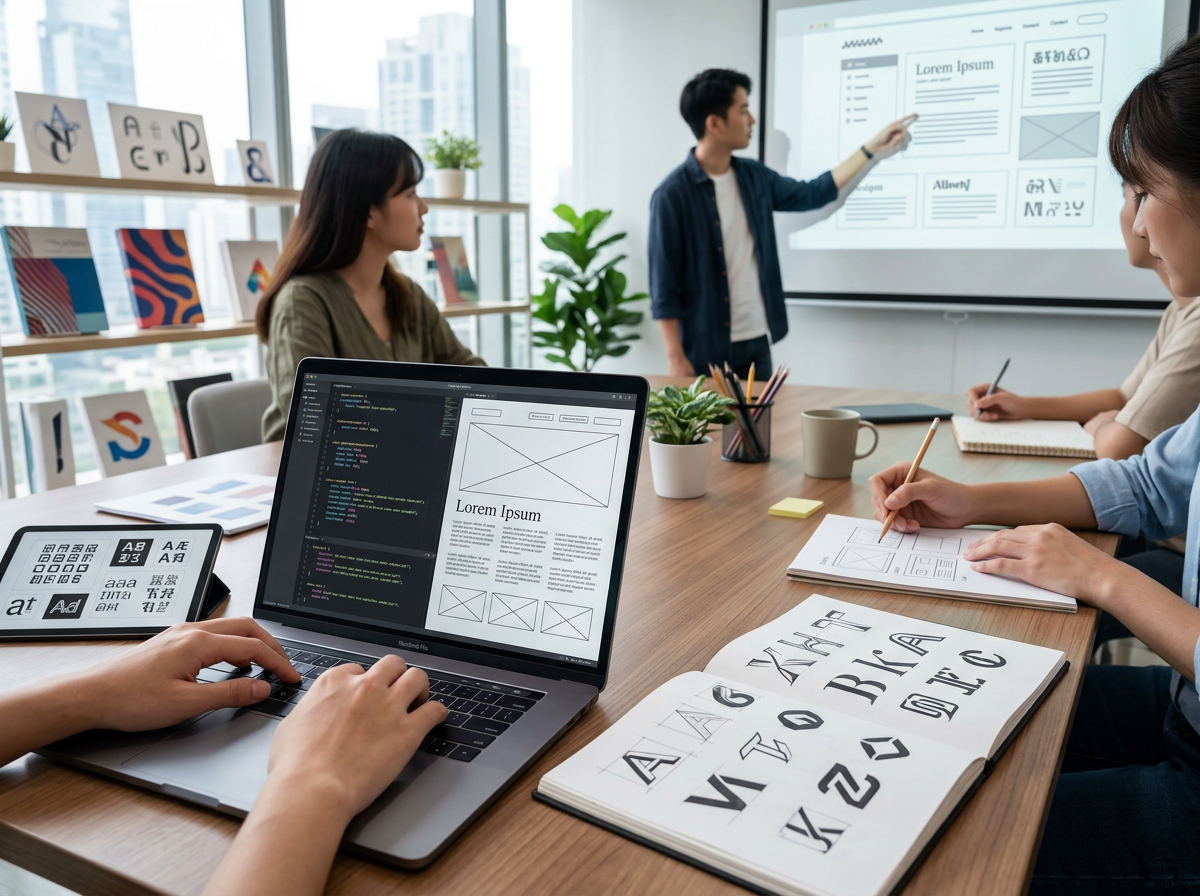
Kostenlose Schriftarten für Webseiten: Effiziente Auswahl und Integration
Der erste Blick auf eine Webseite entscheidet oft über Verweildauer und Nutzererfahrung. Eine passende Typografie prägt diesen Eindruck maßgeblich, vermittelt Professionalität oder Kreativität. Doch die schiere Menge an verfügbaren Optionen überfordert viele Gestalter.
Oftmals greifen Webdesigner zu Standardlösungen, die zwar funktional sind, aber dem Projekt eine individuelle Note verwehren. Die Suche nach der idealen Schriftart, die sowohl ästhetisch ansprechend als auch technisch optimiert ist, erweist sich als zeitaufwendig.
Dieser Leitfaden beleuchtet die Kriterien für die Auswahl kostenloser Schriftarten für Webseiten und zeigt auf, wie diese effizient in digitale Projekte integriert werden. Erfahren, welche Aspekte bei der Typografie für das Web entscheidend sind und wie sich gängige Fehler vermeiden lassen.
Kurz zusammengefasst
- Die Wahl der Webfont beeinflusst die Nutzererfahrung und Markenwahrnehmung erheblich.
- Ladezeiten und Dateigröße sind entscheidende technische Faktoren bei der Schriftauswahl.
- Google Fonts bietet eine umfangreiche Bibliothek mit einfacher Integration.
Welche Kriterien sind bei der Auswahl von Webfonts entscheidend?
Bei der Auswahl von Webfonts sind primär die Lesbarkeit, die Ästhetik und die technische Performance ausschlaggebend. Eine Schriftart muss auf verschiedenen Bildschirmgrößen und Auflösungen gut lesbar sein, um eine optimale Nutzererfahrung zu gewährleisten.
Die Ästhetik einer Schriftart sollte die Markenidentität widerspiegeln und die gewünschte Botschaft visuell unterstützen. Technische Aspekte wie die Dateigröße und die Unterstützung verschiedener Schriftschnitte beeinflussen maßgeblich die Ladezeiten der Webseite.
Lesbarkeit auf unterschiedlichen Geräten
Die Lesbarkeit einer Schriftart auf digitalen Bildschirmen stellt eine fundamentale Anforderung dar. Dies betrifft insbesondere die Darstellung auf mobilen Endgeräten, wo kleinere Schriftgrößen und geringere Auflösungen die Erkennbarkeit erschweren.
Serifenlose Schriften, sogenannte Sans-Serif-Fonts, erweisen sich hier oft als vorteilhafter, da die klaren Linien und das Fehlen von Zierelementen die Lesbarkeit bei geringer Pixeldichte verbessern. Die Buchstabenformen müssen auch in kleinen Punktgrößen klar differenzierbar bleiben.
Ein weiterer Aspekt ist die X-Höhe, also die Höhe der Kleinbuchstaben im Verhältnis zu den Großbuchstaben. Eine größere X-Höhe trägt zur besseren Lesbarkeit bei, da die Buchstabenformen deutlicher hervortreten.
Technische Aspekte und Performance
Die technische Seite der Schriftartenintegration beeinflusst die Ladezeit einer Webseite erheblich. Jede zusätzliche Schriftdatei erhöht das Datenvolumen, das der Browser herunterladen muss, was sich direkt auf die Performance auswirkt.
Optimierte Webfonts, die in verschiedenen Formaten wie WOFF2 vorliegen, reduzieren die Dateigröße signifikant. Die Auswahl von Schriftarten mit nur den benötigten Schriftschnitten – beispielsweise nur Regular und Bold, statt der gesamten Familie – minimiert ebenfalls den Datenverkehr.
Die Implementierung von Font-Display-Eigenschaften wie swap oder fallback in CSS ermöglicht es dem Browser, während des Ladevorgangs der Webfont eine Systemschrift anzuzeigen. Dies verhindert einen unsichtbaren Text (FOIT – Flash of Invisible Text) und verbessert die wahrgenommene Geschwindigkeit.
Praxis-Tipp
Beschränken die Anzahl der verwendeten Schriftfamilien auf maximal zwei, um die Ladezeiten zu optimieren und eine konsistente Designsprache zu gewährleisten. Jede weitere Schriftart erhöht den Ressourcenverbrauch.
Wo finden sich hochwertige kostenlose Schriftarten?
Hochwertige kostenlose Schriftarten finden sich primär auf spezialisierten Plattformen, die eine breite Palette an Designs für unterschiedliche Anforderungen bereitstellen. Diese Quellen bieten oft auch Informationen zu den Lizenzbedingungen, was für die kommerzielle Nutzung unerlässlich ist.
Google Fonts als zentrale Ressource
Google Fonts stellt eine der umfassendsten Bibliotheken für kostenlose Webfonts dar. Die Plattform bietet eine enorme Auswahl an Schriftarten, die sich nach verschiedenen Kriterien wie Stil, Dicke oder Sprache filtern lassen. Die Integration in Webprojekte gestaltet sich hierbei denkbar einfach.
Jede Schriftart bei Google Fonts ist mit einer Open Font License (OFL) versehen, die sowohl die private als auch die kommerzielle Nutzung erlaubt. Dies bietet eine hohe Rechtssicherheit für Entwickler und Designer.
Zudem sind die Schriftarten bei Google Fonts bereits für das Web optimiert, was schnelle Ladezeiten und eine konsistente Darstellung auf verschiedenen Browsern und Geräten gewährleistet. Die Plattform bietet zudem Code-Snippets für die einfache Einbindung.
Wusstest du?
Google Fonts wurde im Jahr 2010 gestartet und hat sich seitdem zu einem der größten Anbieter kostenloser Webfonts entwickelt.
Eine sorgfältige Abwägung von Ästhetik, Lesbarkeit und technischen Anforderungen ist unerlässlich. Google Fonts bietet hier eine hervorragende Ausgangsbasis, doch auch andere Quellen können mit den spezifischen Angeboten punkten, sofern die Lizenzbestimmungen genau beachtet werden.
Durch die Vermeidung gängiger Fehler, wie der übermäßigen Nutzung von Schriftarten oder dem Fehlen von Fallbacks, lässt sich die Qualität einer Webseite signifikant steigern. Letztlich trägt eine optimierte Typografie dazu bei, dass Inhalte effektiv vermittelt werden und Besucher gerne wiederkehren.